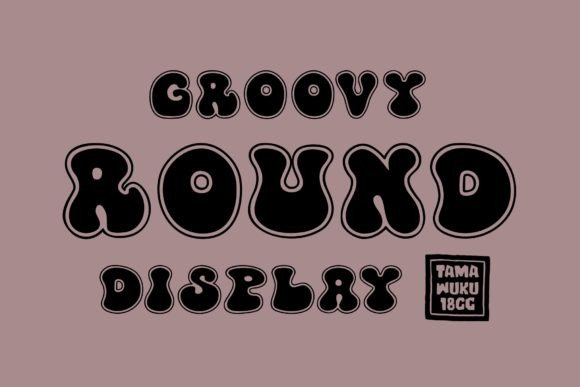
Groovy Round
Поиск подходящих элементов дизайна может быть сложным, но Groovy Round предлагает исключительную коллекцию, которая мгновенно улучшит вашу работу.
Создаете ли вы продукты POD (печать по требованию), свадебные приглашения или графику для социальных сетей, Groovy Round станет идеальным выбором.